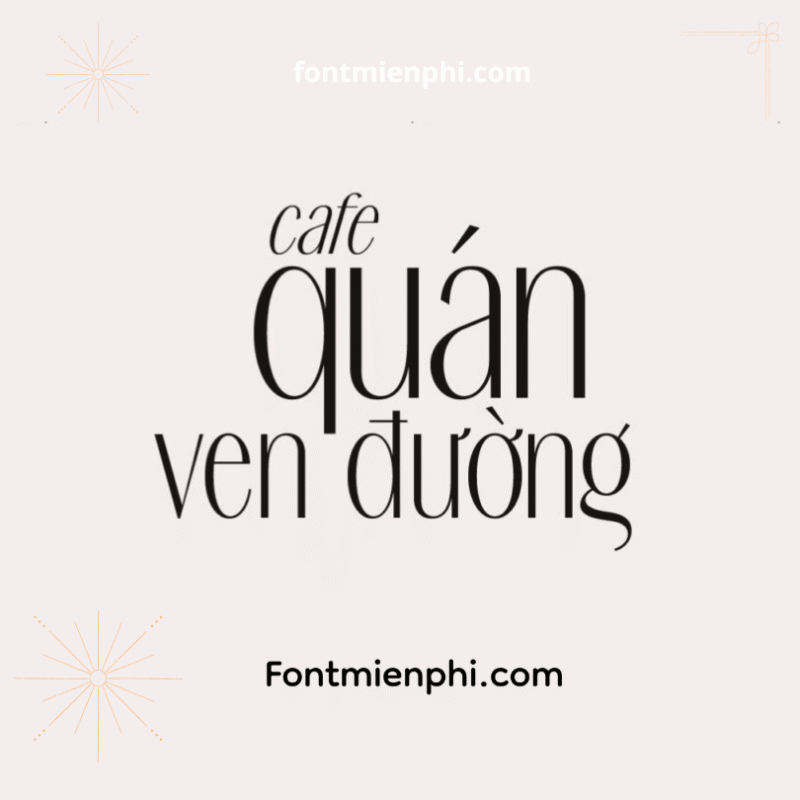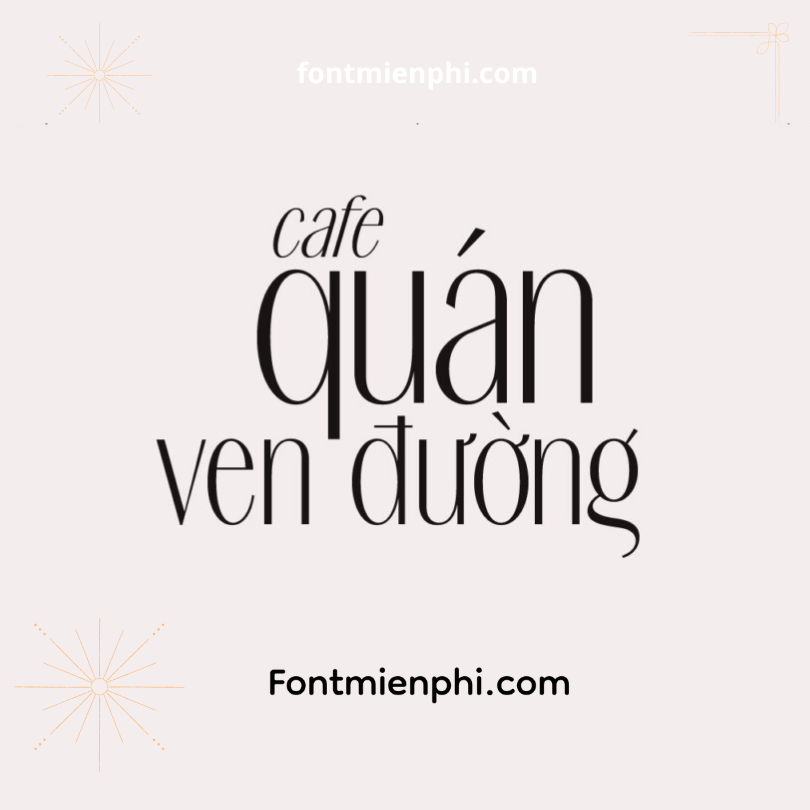
Font Việt hóa 1FTV VIP Signora Regular
Font Việt Hóa 1FTV VIP Signora Regular
Font 1FTV VIP Signora Regular là kiểu chữ sang trọng, tinh tế, được thiết kế dành riêng cho các dự án cao cấp.
Đặc điểm nổi bật:
✔ Hỗ trợ tiếng Việt đầy đủ – Hiển thị sắc nét mọi dấu
✔ Phong cách thanh lịch – Nét chữ mảnh mai, phù hợp thiết kế thời trang, mỹ phẩm
✔ Tối ưu digital – Hiển thị đẹp trên website & mobile
Ứng dụng: Logo, namecard, thiệp mời, banner cao cấp.